10 個最佳在線字體生成器,包括塗鴉字母
已發表: 2022-08-18想像一下。 來自您的目標受眾的用戶正在瀏覽來自不同來源的大量內容。 碰巧您的內容就在其中。 你不想讓觀眾看到你的鏡頭就停下來嗎? 在內容為王的網絡世界中,能夠超越競爭對手並吸引註意力至關重要。
那麼,您如何做到這一點並為自己搶鏡呢? 好吧,您的解決方案當然是利用字體! 字體也是網頁設計中同樣重要的一部分。 您的大腦可能不會有意識地記錄字體如何影響網頁。 但它們仍然會影響我們感知和體驗網站的方式。 如果您沒有預算聘請專業的排版師團隊,那也沒關係。
感謝互聯網,您現在可以使用字體生成器添加自定義字體以增強您的網站。 那麼讓我們來看看現在市場上一些最好的 Webfont 生成器。
最佳在線字體生成器:
創意麵料
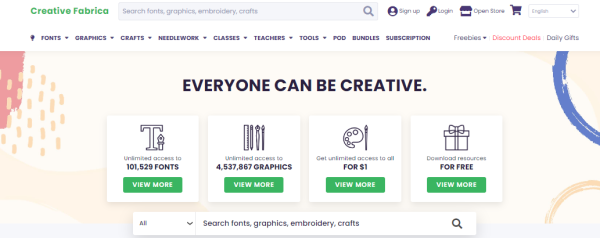
Creative Fabrica 以生產一些最好的工具來提高您的在線創造力和生產力而聞名。 使用他們精美的字體生成器,您現在可以輕鬆生成可用的網絡字體。
此外,這款字體生成器非常易於操作和使用。 您所要做的就是從您的設備中選擇 otf 或 ttf 文件,它會自動將它們轉換為 webfont 包。
Creative Fabrica 的網絡字體生成器的偉大之處在於它可以完全免費地轉換所需的網絡字體。
字體結構
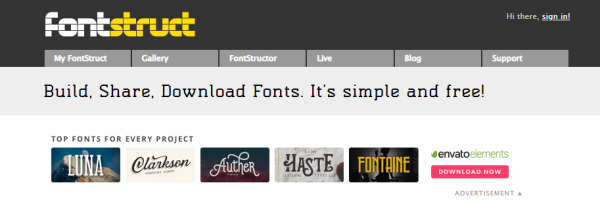
如果您想使用自定義字體增強您的網站,Fontstruct 是可用的最佳網絡字體生成器之一。 另外,它使您可以免費訪問字體。
這是一個真正罕見的工具,因為您通常需要聘請某人使用專業軟件為您創建個人字體。 但是使用 Fintstruct,您可以做同樣的事情而不必擔心錢。
創建自定義字體後,您可以將其作為 TrueType 字體保存到您的設備中。 然後,您可以在您的網站或其他任何地方自由使用它。
但是,如果您沒有時間自己自定義字體,那也沒關係。 您可以搜索現成的字體並使用適合您品牌形象的字體。
Fontstruct 以其古怪的幾何字體而聞名。 因此,網站、小冊子和其他印刷媒體可以利用這一點進行升級。 在他們的資源中,還有一個指南可以幫助您使用這個創新工具。
發光文本
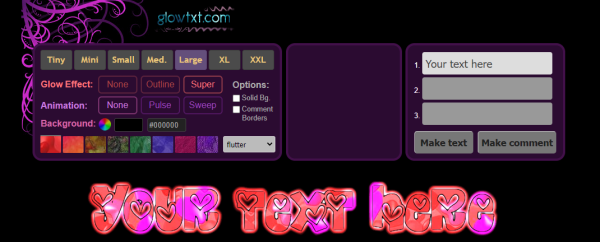
2000 年代初期的氛圍最近一直在流行。 因此,如果您的目標受眾與這種趨勢產生共鳴,Glowtxt 是您的完美花式字體生成器。 它生成的字體非常讓人聯想到 MySpace 和 Disney Channel 的複古設計
此外,它非常簡單、用戶友好,還可以生成吸引人的文本,例如 PNG 或 GIF 文件。
您需要做的就是首先從下拉菜單中選擇尺寸和样式。 然後決定是否需要動畫或發光效果。 最後一步是調整髮光背景顏色並單擊下載按鈕。
如果包含發光效果或動畫,字體將保存為 GIF。 另一方面,如果您決定放棄它,那麼它將以 PNG 文件的形式下載到您的設備中。
如果你想建立一個有趣和樂觀的形象,你一定要看看 Glowtxt。 它是一款非常酷的字體生成器,也很容易吸引年輕觀眾。
字體生成器
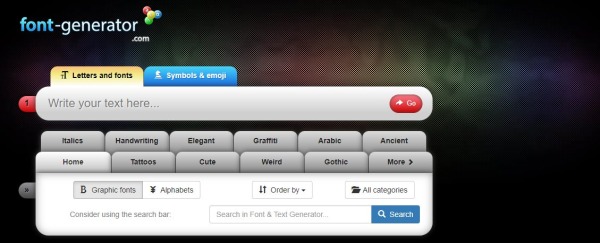
您的內容是否適合復古美學? 如果是,那麼不要再看了,因為這正是 Font Generator 提供的。
至關重要的是,您創建的任何內容都能吸引觀眾的眼球並吸引他們。使用字體生成器是挑選出肯定會引起注意的最佳字體的好方法。 您還可以使用自定義項來添加您自己的個人風格。 字體生成器有多種設計和尺寸可供選擇,是您隨身攜帶的絕佳工具。
它是一款精美的字體生成器,可讓您從多種類別中進行選擇。 此外,您還可以瀏覽每個類別下的幾種樣式。 類別包括手寫、優雅、哥特式等。
因此,您可以單擊任何人並調整字體大小、顏色和背景。 然後,您可以將字體下載為 PNG、JPG 或 GIF 文件。
字體生成器因其各種書法、復古和優雅的字體而非常受歡迎。 只需單擊一下,您就可以使用大量圖形字體。
紋身字體生成器
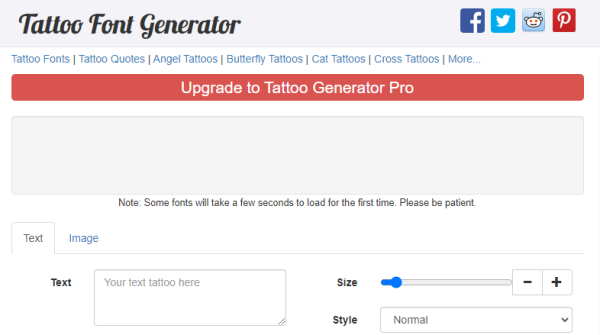
紋身工作室和紋身愛好者也可以從使用平台紋身字體生成器中受益。 由於每個客戶都會想到特定的設計,因此字體生成器將幫助您更快地勾勒出他們的設計。 這也讓他們有機會發揮他們的創造力。
這個特定的紋身字體生成器也是一個獨特的平台,提供創意和前衛的紋身字體。 任何人都可以輕鬆操作此字體生成器,因為界面也非常人性化。
您需要做的就是首先在文本框中添加所需的文本。 然後,您可以瀏覽他們大量的字體並選擇您喜歡的字體。 您還可以使用弧線、方向、大小、樣式、前景色和背景色。 他們所有的字體都可以免費用於商業用途。
此外,紋身字體生成器可讓您通過右鍵單擊並選擇“打印”選項直接打印設計。 您甚至可以將其以 PDF 格式保存到您的設備中。
燃燒的文字
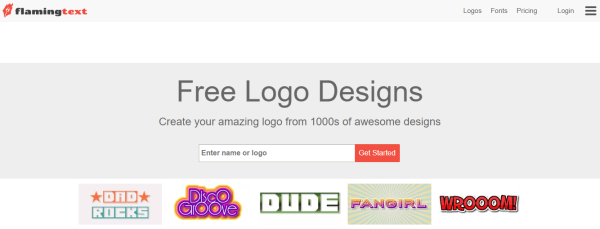
Flaming Text 提供了所有可以通過瀏覽器訪問的免費設計工具。 所以不需要下載或安裝。
Flaming Text 工具還包括最易於使用的酷字體生成器之一。 它使您可以從各種模板創建有吸引力的徽標和橫幅。
您只需輸入文本,從一系列可用的字體樣式中進行選擇,然後瀏覽進一步的自定義設置。 然後,您可以將新設計的字體作為 PNG 文件下載到您的設備。 就如此容易。
如果您不想自己自定義,也可以從他們預先設計的模板中進行選擇。 這些模板帶有已經為您設置的不同顏色、漸變效果和背景顏色。
有很多款式可供選擇。 因此,您可以確保找到一個適合您想要的圖像的產品。 Flaming Text 是一款很棒的精美字體生成器,適合那些希望將焦點放在其內容上的人。 有趣而充滿活力的設計也讓 Flaming Text 成為博主的好選擇。
字形
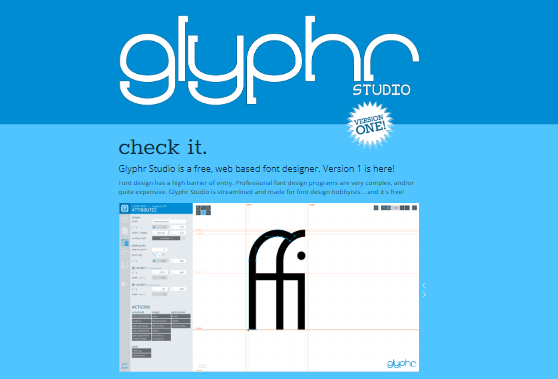
Glyphr 的界面允許您為您的業務創建令人驚嘆的自定義字體。 這就是為什麼它被認為是市場上非常流行的字體生成器。 它旨在通過緊跟最新趨勢來提供無縫的用戶體驗。
與高級字體工具類似,Glyphr 還允許您借助其“句柄”調整每個像素。
學習如何操作 Glyphr 絕對值得。 一旦你知道你的方式,可能性是無窮無盡的。 Glyphr 是一個非常通用且靈活的網絡字體生成器。 因此,您可以找到為您的網站創建高質量自定義字體所需的所有工具。
Glyphr 還為那些不想自己創建字體的人提供了一些現成的字體。
它是一個多方面的字體工具,非常適合製作更傳統的字體。 其他字體工具提供有趣和前衛的氛圍。 但是 Glyphr 提供了適合商業的字體。
字體模因
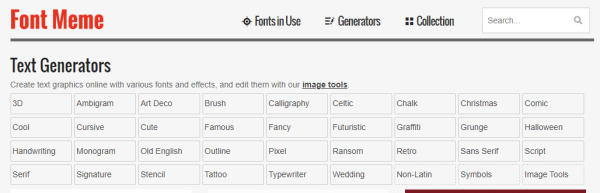
許多人經常回憶起他們遇到的流行品牌和電視節目中的特定字體。 使用這些字體可以讓您在其他競爭對手中佔據優勢。
這是因為觀眾自然會傾向於他們熟悉的字體。 畢竟,沒有什麼比熟悉更能帶來溫暖的舒適感了。 如果您使用這些字體,他們將更有可能點擊特定內容。
Font Meme 是一個完全免費的在線字體生成器。 您可以使用它來創建受大眾喜愛的標誌性徽標和品牌啟發的有吸引力的字體。
有很多免費字體可供選擇。 您可以瀏覽它們並選擇您喜歡的一個。 然後玩自定義並單擊“生成”。 但是,如果您遇到您真正喜歡的高級字體,您可以點擊購買並返回 Font Meme 上傳和使用它。
Font Meme 是一款理想的精美字體生成器,用於創建需要流行媒體來源字體的海報和營銷內容。
Instagram 字體
如今,許多企業正在轉向社交媒體來推銷他們的產品和服務。 尤其是 Instagram,它有很大的潛力讓品牌和企業爆發。
Instagram 字體專門設計用於提供可以優化您的 Instagram 供稿的字體。 他們的選擇包括某些字體和字體,這些字體和字體因其引人注目的風格而在 Instagram 上流行。
因此,您可以輕鬆地使用這些字體來提升您在 Instagram 上的內容。 但這還不是全部。 如果你經營一個網站,你也可以在那裡使用字體。
您只需在輸入空間中輸入文本,Instagram Fonts 就會拉出一系列字體選項。 確定字體樣式後,您可以將其複制並粘貼到您的 Instagram 簡歷或標題上。
最好的部分是這些字體在所有設備上都兼容,無論您使用的是 android、iPhone 還是 PC。
Instagram Fonts 是一款理想的字體生成器,可用於增強 Instagram、Facebook 和其他社交媒體平台上的內容。 他們的設計非常獨特和有吸引力。 因此,他們肯定會讓您與 Instagram 上的其他業務區分開來。
字體空間
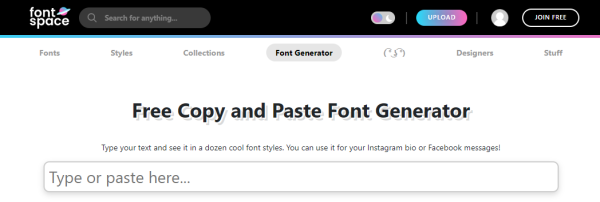
由於您需要將所有工作放入內容中,有時您只需要一個簡單的字體生成器即可對字體進行排序。
Font Space 是一款非常酷的字體生成器,因其用戶友好的界面而廣受歡迎。 它允許您插入文本並立即將其直接從他們的網站複製到您的網站。
此外,所有字體都採用 Unicode 樣式。 這意味著無論您使用什麼設備,您都可以安全地避免兼容性問題。
Font Space 可幫助您為您的社交媒體頁面和網站帶來驚人的光彩。 您還可以使用它來為您的標題和引語增添趣味。 它是無憂無慮的,並使用整潔和流行的字體為您的內容提供優勢。
此工具非常適合為您的社交媒體帳戶撰寫字幕和 DM。 與其他 webfont 生成器不同,Font Space 提供了更微妙的樣式,非常適合句子和段落。 它可能沒有那麼響亮和引人注目,但它肯定會讓你與眾不同。
結論:
排版是每個品牌都應該認真思考的營銷策略。 這是設計和排列類型以使您的內容更具吸引力的藝術。
通過使用我們列表中的任何字體生成器,您可以為您的徽標、網站或社交媒體創建引人注目的自定義字體。
您甚至不需要了解 Photoshop矢量或複雜的網頁設計技術。 您只需單擊幾下即可完成所有工作。 在自定義字體後,您可以專注於為您的內容生成潛在客戶。
那你還在等什麼? 今天就開始使用這些很酷的字體生成器!